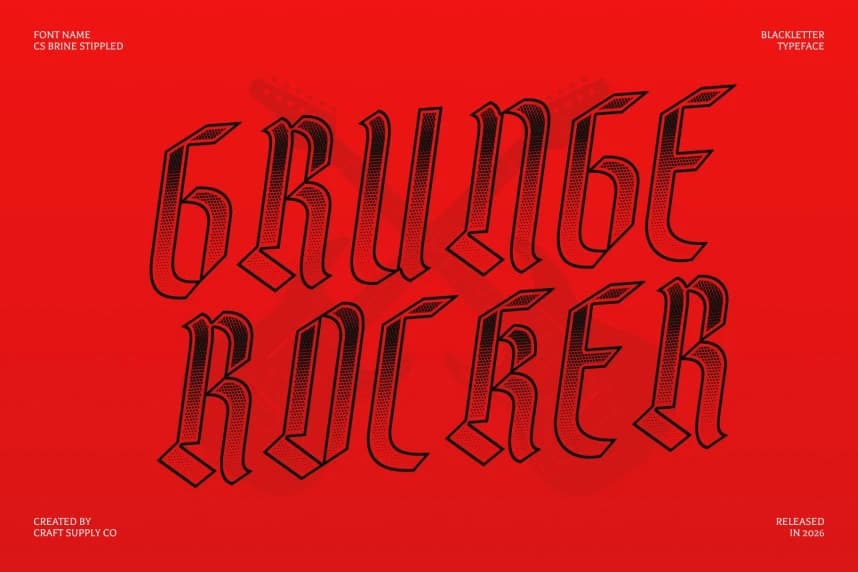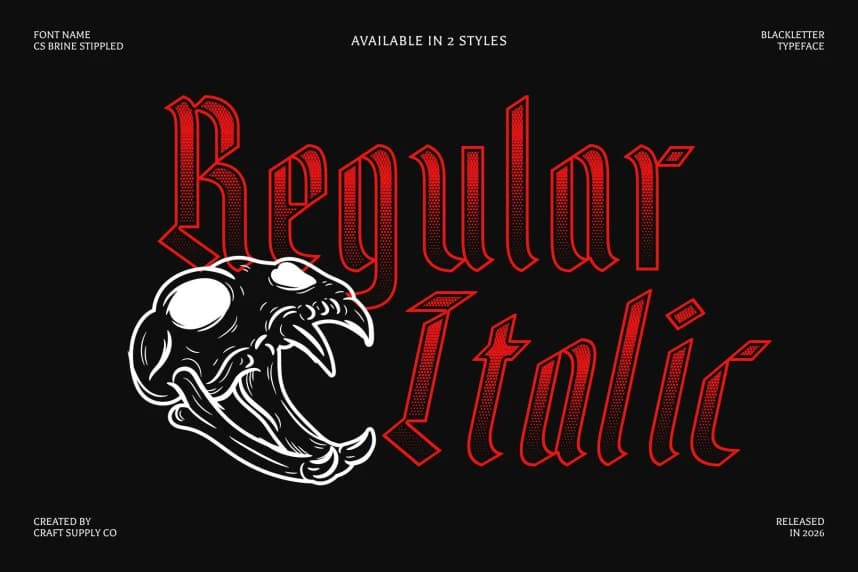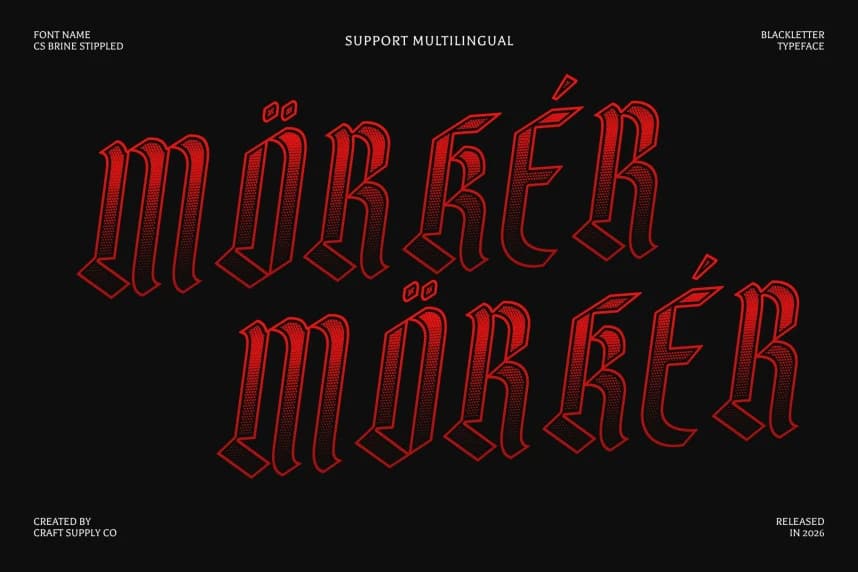
CS Brine Stippled Font
CS Brine Stippled Font – Tarihi Zarafete Sahip Blackletter Yazı Tipi; Doku Derinliğine Sahip Özenle İşlenmiş Blackletter. Bu, zengin ayrıntılı harf biçimleri ve kalın, keskin hatlarla büyüleyen etkileyici bir gösteri yazı tipidir.
CS Brine Stippled Font – Blackletter Font ile Tarihsel Zarafet, Dokulu Derinliğe Sahip Özenle Tasarlanmış Blackletter. Bu, zengin detaylı harf biçimleri ve kalın, keskin hatlarla büyüleyen çarpıcı bir Blackletter gösterim yazı tipidir.